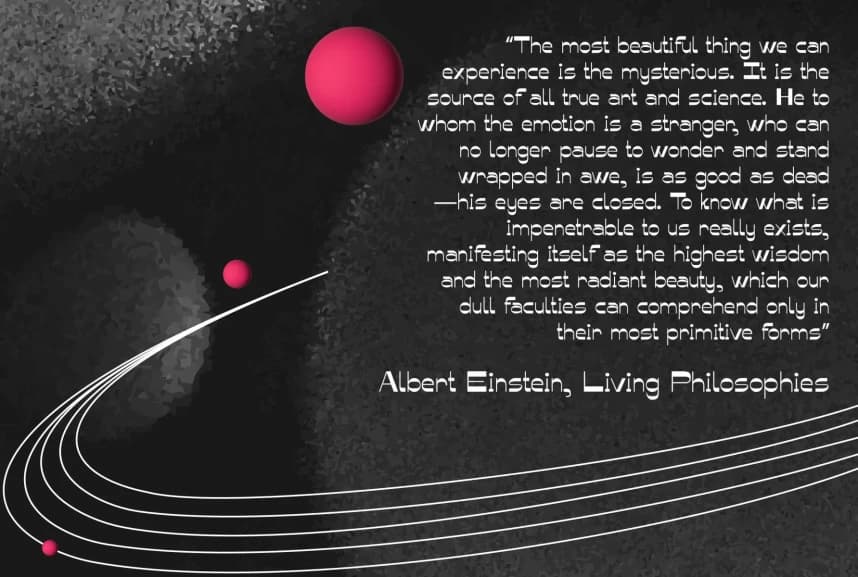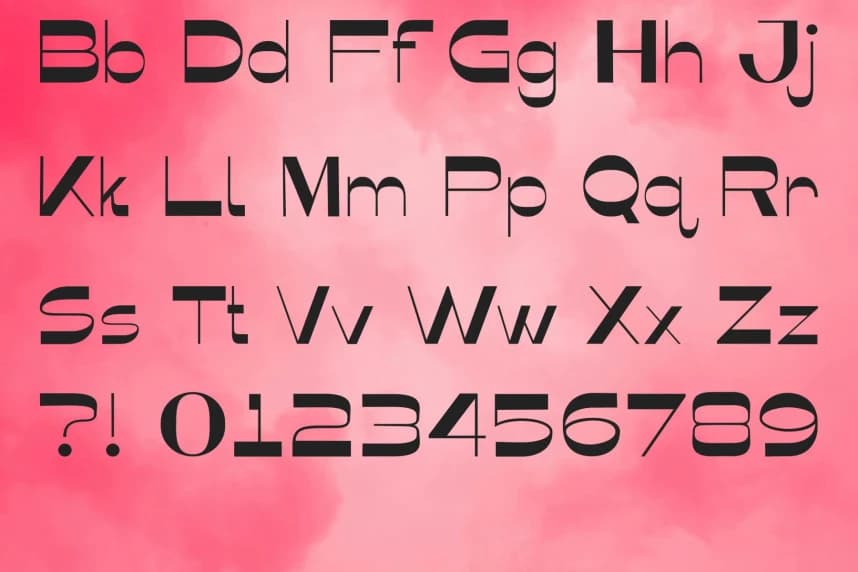
Dark Saliana Yazı Tipi
Dark Saliana Font, Cerasus Creative Studios tarafından sunulan kutu biçimli, geometrik ve fütüristik bir yazı tipidir. Dark Saliana yazı tipini kullanmadan önce LICENSE.txt dosyasındaki Son Kullanıcı Lisans Sözleşmesi'ni inceleyin. Geçerli bir lisans olmadan yazı tipinin kullanılması yasal sonuçlara
Dark Saliana Font, Cerasus Creative Studios'dan gelen kutu görünümlü, geometrik ve fütüristik bir yazı tipidir. Dark Saliana Font'ı kullanmadan önce LICENSE.txt dosyasındaki Kullanıcı Lisans Sözleşmesini incelemenizi rica ederiz. Geçerli bir lisans olmadan bu yazı tipinin kullanımı yasal sonuçlara yol açabilir.